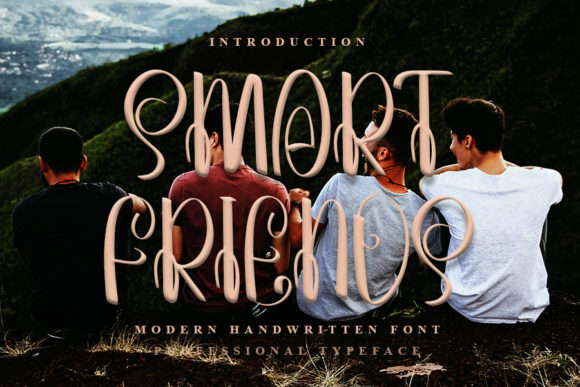
Creativefabrica Smart Friends Font
[Creativefabrica] Smart Friends Font
Умные друзья - это причудливый и уникальный рукописный шрифт, который легко выделяется на фоне других.
Простой, но с сильным визуальным эффектом, этот шрифт мгновенно сделает ваше творение более привлекательным, чем любое другое.